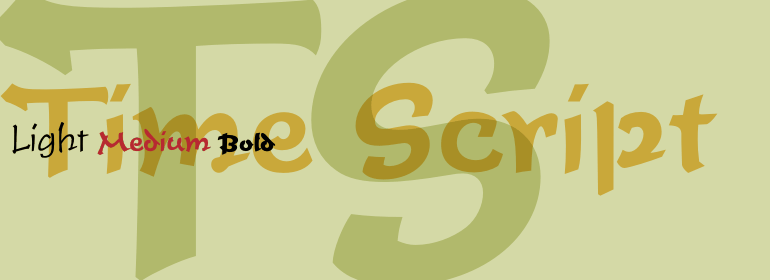
Time Script™
Time Script™,这款字体结构工整、笔画清晰,兼顾美观与易读性,适用于标题、正文、海报、包装、LOGO 等多种场景。字形优雅稳定,风格百搭耐看,适配日常排版与创意设计,让文字呈现更舒适、更具质感。Time Script™一笔一画,皆是细节,以均衡的比例、流畅的线条打造舒适视觉体验,字形端正大气,风格简约现代。无论是商业设计、品牌宣传还是日常排版,都能轻松驾驭,让文字更有格调与力量。Time Script™字体下载。
字体品牌: Linotype(Monotype) 设计师:Trump,Georg 字体分类: 字体属性:外文 字符集:Unicode 发布时间: 2018